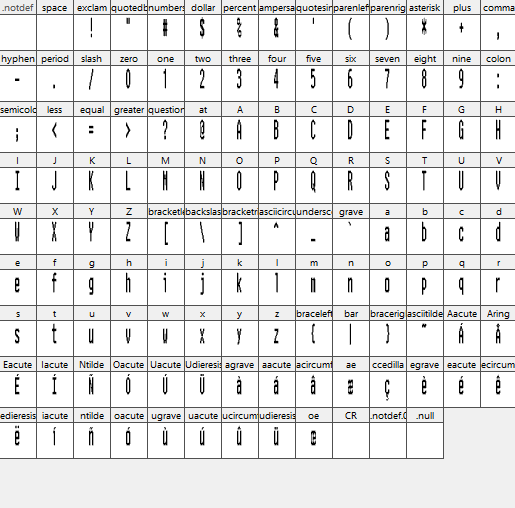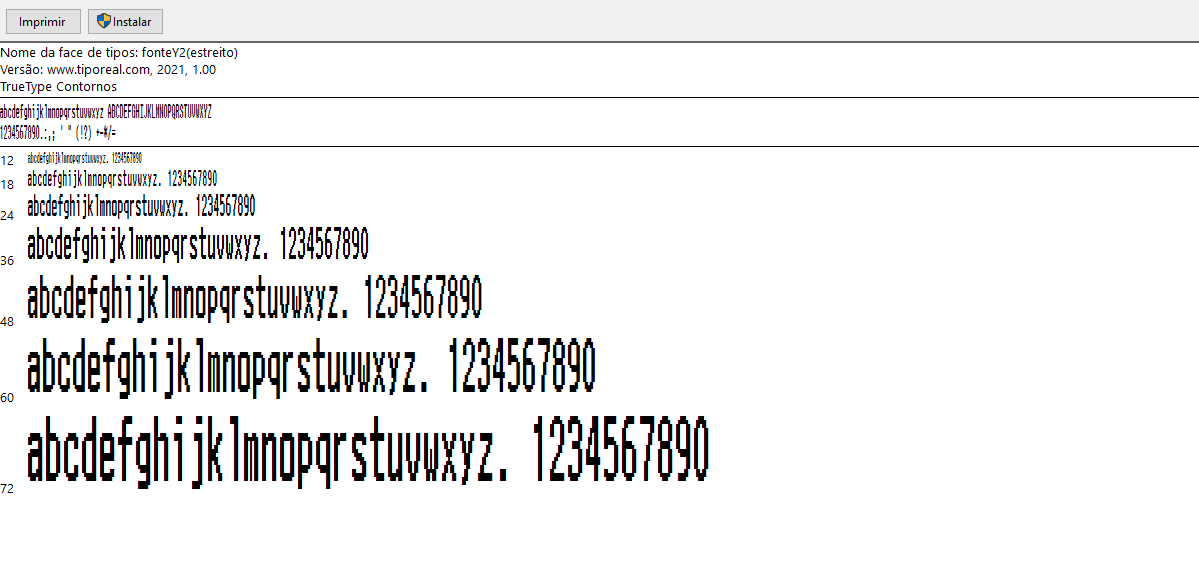
Todos os personagens⤴
O que parece quando aberto com o visualizador de fontes padrão do Windows⤴
Fonte de cupom fiscal, tipografia de fatura simplificada, fonte de impressora térmica recibo, tipografia de nota fiscal
Todos os personagens⤴
O que parece quando aberto com o visualizador de fontes padrão do Windows⤴